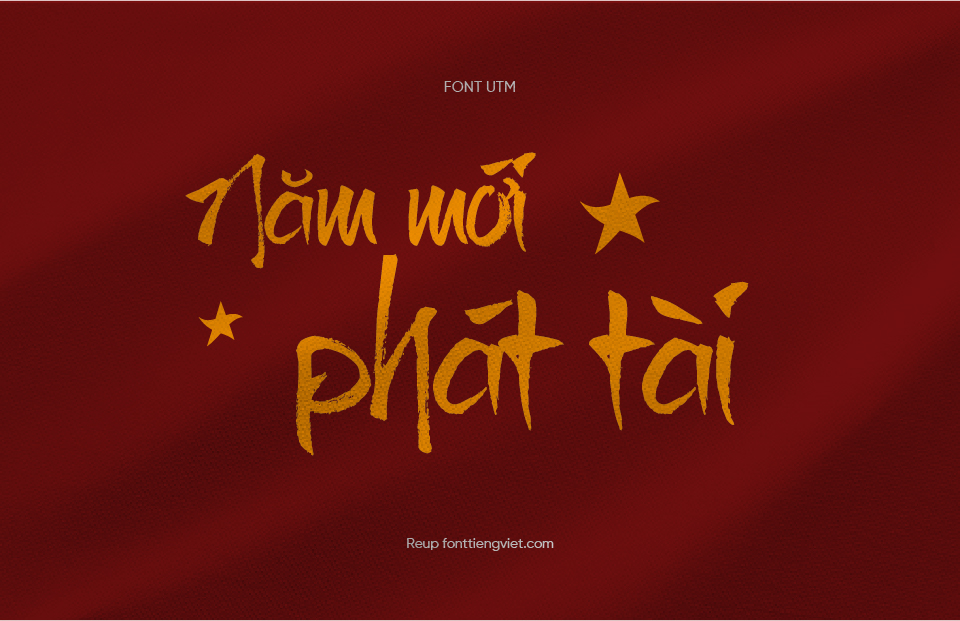
Giới thiệu về bộ Font việt hóa UTM Brushtip-C – Tết
Chào đón năm mới với những phong bao lì xì hay banner rực rỡ là nhu cầu tất yếu của mỗi người làm sáng tạo. Trong đó, việc lựa chọn Font Chữ đóng vai trò quan trọng để tạo nên linh hồn cho tác phẩm. Font việt hóa UTM Brushtip-C – Tết chính là giải pháp hoàn hảo mang lại vẻ đẹp phóng khoáng, mạnh mẽ nhưng không kém phần uyển chuyển. Đây là kiểu chữ mô phỏng nét bút lông thủ công, cực kỳ phù hợp cho các chủ đề mang tính truyền thống và lễ hội tại Việt Nam.
Đặc điểm nổi bật của Font việt hóa UTM Brushtip-C – Tết
Nét chữ nghệ thuật và đậm chất thủ công
Được thiết kế với các đường nét dày dặn và hiệu ứng xước tự nhiên, bộ chữ này tái hiện chân thực cảm giác như đang viết bằng mực tàu trên giấy điệp. Sự thô mộc của nó giúp các thiết kế trở nên gần gũi và ấm áp hơn trong không khí sum vầy của ngày Tết.
Khả năng tương thích và tối ưu hóa
Phiên bản Font việt hóa UTM Brushtip-C – Tết đã được chỉnh sửa kỹ lưỡng để hỗ trợ đầy đủ bảng mã tiếng Việt. Người dùng có thể dễ dàng sử dụng trên các phần mềm đồ họa chuyên nghiệp như Photoshop, Illustrator hay thậm chí là các ứng dụng thiết kế đơn giản trên điện thoại mà không lo bị lỗi font hay mất dấu.
Ứng dụng thực tế trong thiết kế sự kiện Tết
Bạn có thể sử dụng bộ chữ này để thiết kế tiêu đề cho thiệp chúc mừng, nhãn dán quà tặng hoặc các câu đối đỏ treo tường. Với phong cách độc đáo, nó giúp thông điệp của bạn trở nên nổi bật và thu hút sự chú ý ngay từ cái nhìn đầu tiên. Hãy kết hợp với các gam màu đỏ, vàng để phát huy tối đa giá trị thẩm mỹ mà bộ chữ này mang lại cho không gian học đường và gia đình.